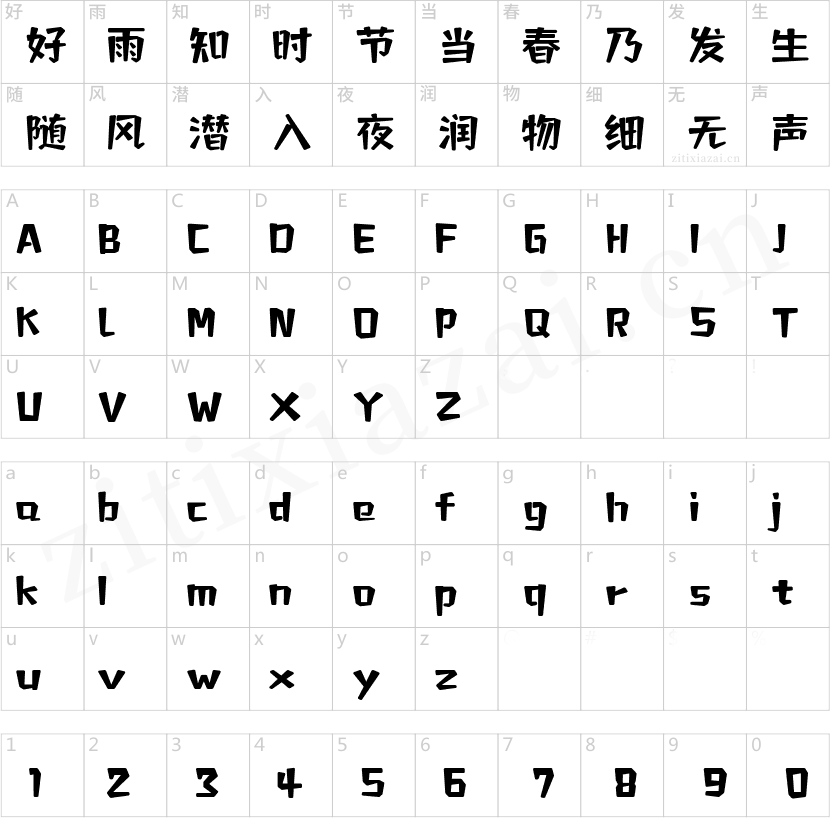
字魂227号-萌趣萝卜体
字魂227号-萌趣萝卜体,这款字体结构工整、笔画清晰,兼顾美观与易读性,适用于标题、正文、海报、包装、LOGO 等多种场景。字形优雅稳定,风格百搭耐看,适配日常排版与创意设计,让文字呈现更舒适、更具质感。字魂227号-萌趣萝卜体一笔一画,皆是细节,以均衡的比例、流畅的线条打造舒适视觉体验,字形端正大气,风格简约现代。无论是商业设计、品牌宣传还是日常排版,都能轻松驾驭,让文字更有格调与力量。字魂227号-萌趣萝卜体字体下载。
字魂字体字小魂萌趣萝卜体字体是由字魂创意字库设计并生产的一款可商用的字体,被收录于字小魂系列。该字体支持GB-2312标准,包含6765个中文、字母、符号和数字,字体类型偏向创意字体,具有可爱、简约、时尚的风格,在市面上广泛用于活动促销、广告电商、广告等场景。